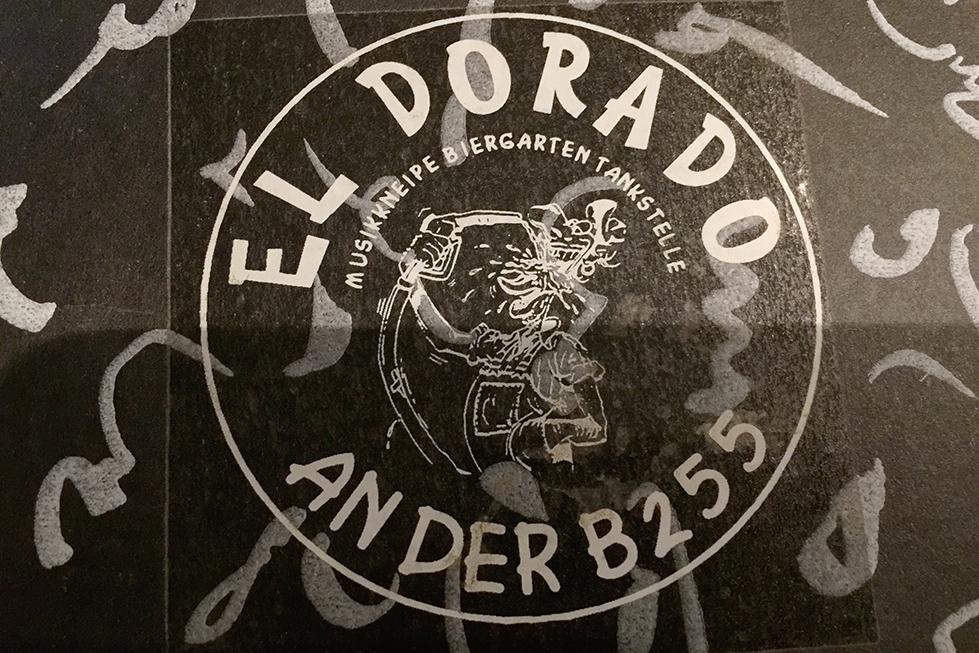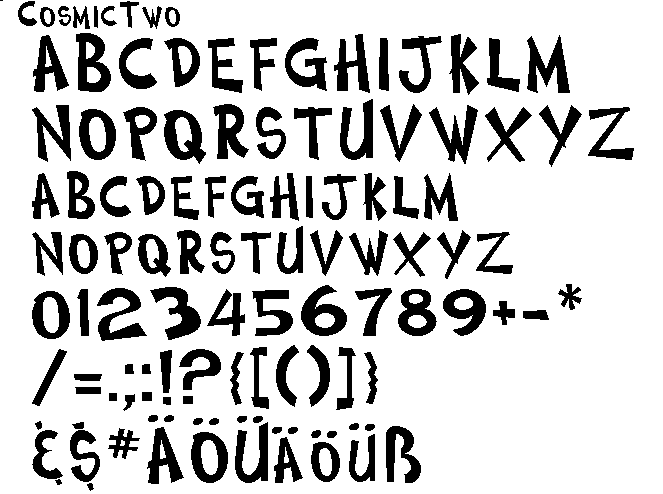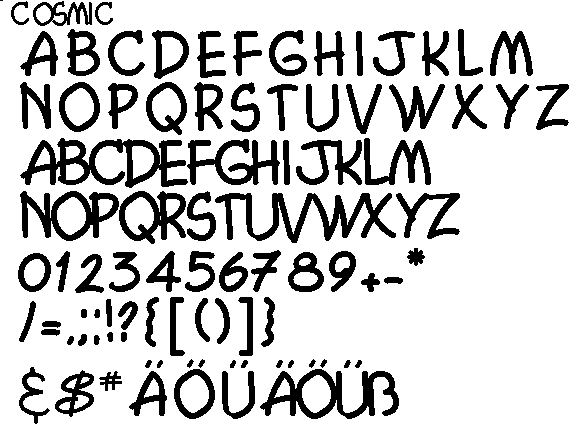
Suche Schriftart von »EL DORADO«-Aufkleber
Meine Frau hatte vor langer Zeit (90er Jahre) mal eine Biker-Kneipe gepachtet. Aus dieser Zeit gibt es noch einen Aufkleber; keine Ahnung, wer den damals entworfen hatte. Es soll hier auch keine Analyse oder Bewertung des Designs erfolgen, aber aus nostalgischen Gründen und einem sehr konkreten und leider auch sehr traurigen Anlass suchen wir nun die Schrift des Kneipennamens »EL DORADO«.
Hatte schon den Aufkleber abfotografiert, die einzelnen Buchstaben ausgeschnitten, geradegestellt, gesäubert, neu montiert und bei WhatTheFont hochgeladen. Leider kein passgenauer Treffer dabei :-(
Jetzt hoffe ich auf einen Geistesblitz aus der Typo-Gemeinde …
PS: Die Schnirkel im Hintergrund gehören zum Cover der Mappe, auf die der ansonsten transparente Aufkleber aufgeklebt worden ist.
Die Engcomica, gefunden auf dafont.com im Bereich Extravagant > Comic, kommt der Sache schon relativ nahe, ist es aber leider nicht genau … :-(
Naja, wenn es nicht gelingt, die richtige Schrift zu finden (oder es sie schlichtweg nicht gibt), wird es wohl die Engcomica werden.
Noch jemand 'ne Idee zur Schrift von »AN DER B255« vielleicht?
vor langer Zeit (90er Jahre)
das hört sich nach irgendeiner typischen Sammlung an :-? Müsste man mal bei den Verdächtigen, wie CorelDraw, durchgucken oder jemanden Fragen, der sich damit auskennt, @Uwe Borchert
Es soll hier auch keine Analyse oder Bewertung des Designs erfolgen, aber aus nostalgischen Gründen
Das wäre wohl ein Laden, wo ich gerne mal angehalten hätte :roll:
ich wühle mal wieder auf Schnitzels Anregung in der Corel-Sammlung mit den vielen Bitstream-Schriften.  Ich bin vmtl. fündig geworden. Das El Dora könnte die Cosmic2 sein, das da drunter die Cosmic.
Allerdings finde ich diese Schriften erst mal nicht auf Identifont, daher auch meine eigenen Vorschaubildchen aus der Sammlung.  Aber auch auf Myfonts finde ich die Beiden nicht. Auch im Showcase von Luc D. tauchen die beiden nicht auf: